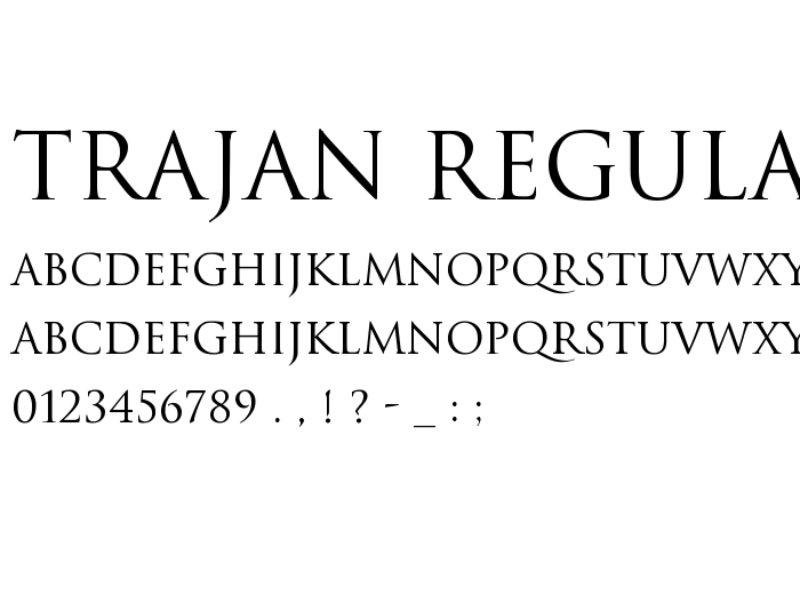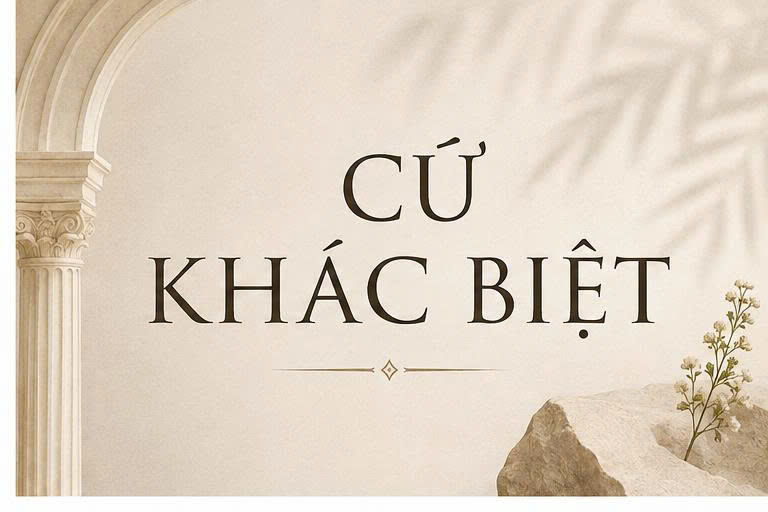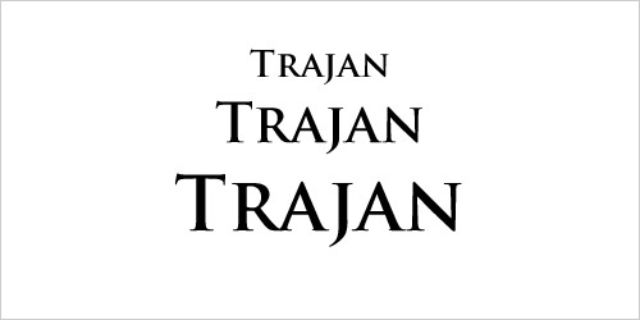
Font Trajan Pro Việt hóa là bộ phông chữ thuộc dòng Classical Inscriptional Serif lừng danh do Carol Twombly thiết kế cho Adobe, lấy cảm hứng từ những ký tự đục khắc trên cột đài Trajan tại Rome từ năm 113 sau Công nguyên. Nổi tiếng toàn cầu với tư cách là biểu tượng của điện ảnh Hollywood và các công trình mang tính biểu tượng lịch sử, Trajan Pro 3 là chất liệu trực quan tuyệt vời để các kiến trúc sư, nhà thiết kế kiến tạo chiều sâu tôn nghiêm cho các bản vẽ phối cảnh biệt thự tân cổ điển, cổng chào khu nghỉ dưỡng hay bìa hồ sơ năng lực dự án.
Tỷ lệ vàng bia đá La Mã và khí chất điện ảnh của font Trajan Pro Việt hóa
Điểm cuốn hút của font Trajan Pro Việt hóa nằm ở cấu trúc hình thể được đúc kết từ hình học cổ đại, nơi các đường thẳng dứt khoát kết hợp cùng chân chữ (serif) vuốt nhọn tinh tế mô phỏng vết đục của lưỡi búa trên đá hoa cương. Tỷ lệ các ký tự in hoa được căn chỉnh theo tỷ lệ vàng, mang lại vẻ ngoài đĩnh đạc, uy nghi và đượm chất sử thi cho từng dòng tiêu đề.
Sự ổn định về mặt thị giác của dòng font này giúp khẳng định vị thế, sự minh bạch và uy tín vững chắc của đơn vị chủ trì công trình. Khi xuất hiện trên các bề mặt vật liệu kiến trúc sang trọng như đá tự nhiên cẩm thạch xám, kim loại đồng đúc, vách kính mờ hay gỗ lim sẫm màu trong các căn nhà lắp ghép tân cổ điển, Trajan Pro tạo nên sự hòa quyện thẩm mỹ vô cùng bề thế.
| Phân loại phong cách | Roman Inscriptional / Monumental Serif / Cinematic |
| Nhóm phông tiêu biểu | Trajan Pro, Trajan Pro 3, SVN-Trajan Pro |
| Mục đích phù hợp | Bia đá kỷ niệm, cổng chào villa, bìa hồ sơ dự án |
Tư vấn từ chuyên viên: Trajan Pro sở hữu phong thái trang trọng của văn bia cổ đại. Để bản thiết kế đạt hiệu quả thẩm mỹ tốt, bạn nên sử dụng phông chữ này cho các tiêu đề chính, tên công trình hoặc các câu khẩu hiệu ngắn.
03 Ứng dụng phông chữ Trajan Pro vào công trình thực tế
Nhờ vẻ ngoài uy nghi và tính biểu tượng mạnh mẽ, bộ phông chữ này mang lại giá trị thực tế lớn trong khâu tạo điểm nhấn cho các công trình hiện đại:
- Cổng chào và Biển tên mặt tiền Biệt thự Tân cổ điển: Những nét chạm khắc sắc nét của Trajan Pro rất ăn ý khi gia công chữ nổi bằng đồng đúc hoặc khắc chìm trên bia đá tự nhiên, giúp mặt tiền căn nhà lắp ghép toát lên vẻ bề thế và quý phái.
- Bìa hồ sơ năng lực dự án kiến trúc: Sử dụng font Trajan Pro Việt hóa cho tên dự án và tiêu đề các chương mục giúp tập hồ sơ trông như một ấn phẩm nghiên cứu học thuật chuẩn mực, tạo niềm tin lớn với các chủ đầu tư.
- Hệ thống biển chỉ dẫn khuôn viên và Tên phân khu: Phông chữ này khi gia công trên vật liệu kim loại sơn tĩnh điện hoặc mica gương sẽ giúp không gian sảnh đón tiếp toát lên chất nghệ thuật thanh lịch và sang trọng.
03 Lưu ý bố cục Trajan Pro Bold giữ trọn vẻ uy nghiêm và sắc sảo
Để khai thác hiệu quả vẻ đẹp của dòng font bia đá La Mã này mà không gây cảm giác nặng nề cho bản vẽ, người thiết kế nên lưu tâm một số kinh nghiệm sau:
- Nới rộng khoảng cách ký tự: Chữ La Mã được thiết kế để hiển thị đẹp khi các con chữ có khoảng thở thoáng đãng. Bạn nên tăng nhẹ khoảng cách giữa các chữ cái khi viết hoa toàn bộ để bố cục mang đậm phong thái điêu khắc cổ đại.
- Hạn chế dùng cho văn bản dài: Do cấu trúc chân chữ nhọn và thường là dạng chữ in hoa (All-Caps hoặc Small-Caps), việc sử dụng Trajan Pro Bold cho các đoạn thuyết minh kỹ thuật dài sẽ làm giảm tốc độ đọc hiểu. Hãy giới hạn trong các tiêu đề từ 2 đến 5 từ.
- Lựa chọn gam màu vương giả: Trajan Pro phát huy hiệu quả thị giác cao khi phối cùng các tông màu mang sắc thái cổ kính như vàng ánh kim, xanh ngọc bích đậm, đen tuyền hoặc xám đá tự nhiên trên nền vật liệu nhám mờ.
2. Phông chữ Trajan Pro 3 có điểm gì khác biệt so với bản Trajan Pro gốc?